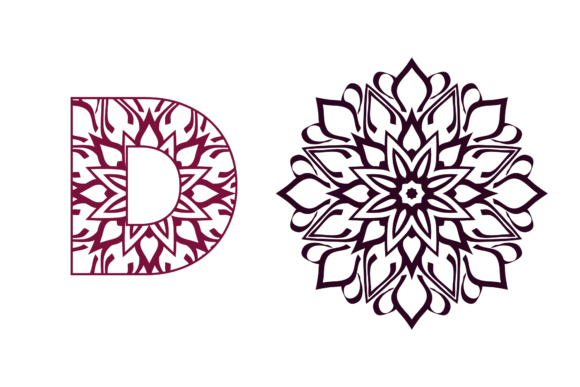
Mandala Font Alphabet D Vector
Mandala Font Alphabet D Vectorのような高品質の素材をお探しの場合、このプレミアムパッケージはクリエイティブなプロジェクトに素晴らしい選択です。
精密に作られたMandala Font Alphabet D Vectorは、クリーンなベクター、滑らかなタイポグラフィ、そして安心のための商用ライセンスを提供します。